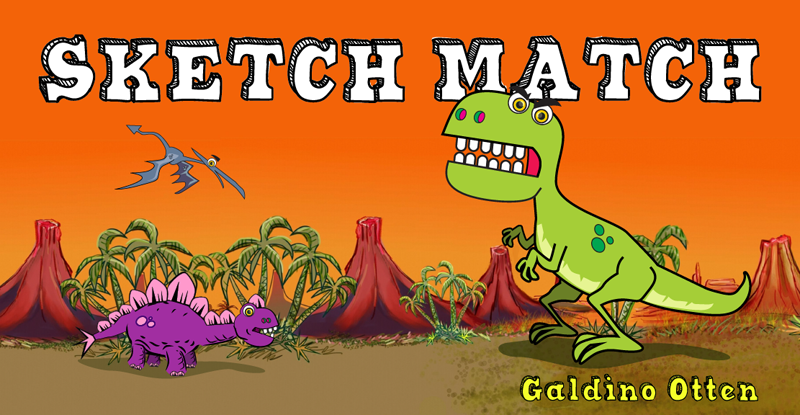
A fonte Sketch Match é uma escolha ótima para quem busca um equilíbrio entre modernidade e elegância na tipografia. Essa fonte foi projetada pelo designer Hamilton, oferecendo uma variedade de estilos que vão desde linhas retas e clean até seções arredondadas e mais afetuosas, tudo em um só arquivo compacto. Perfeita para criações visuais variadas como banners, ícones ou design de logotipos, Sketch Match traz uma fidelidade impressionante ao texto. Suas formas fluidas combinam bem com o estilo minimalista moderno do design gráfico atual, e ainda oferece um grau apropriado de personalização para adaptar-se às necessidades específicas de cada projeto. Com suas linhas suaves e sua tipografia clean, Sketch Match é uma escolha inteligente tanto para designers que buscam equilíbrio entre modernidade e simplicidade quanto para aqueles que desejam estilos mais elaborados. É a fonte perfeita para quem procura um conjunto de recursos com qualidade superior para atender às suas necessidades específicas.